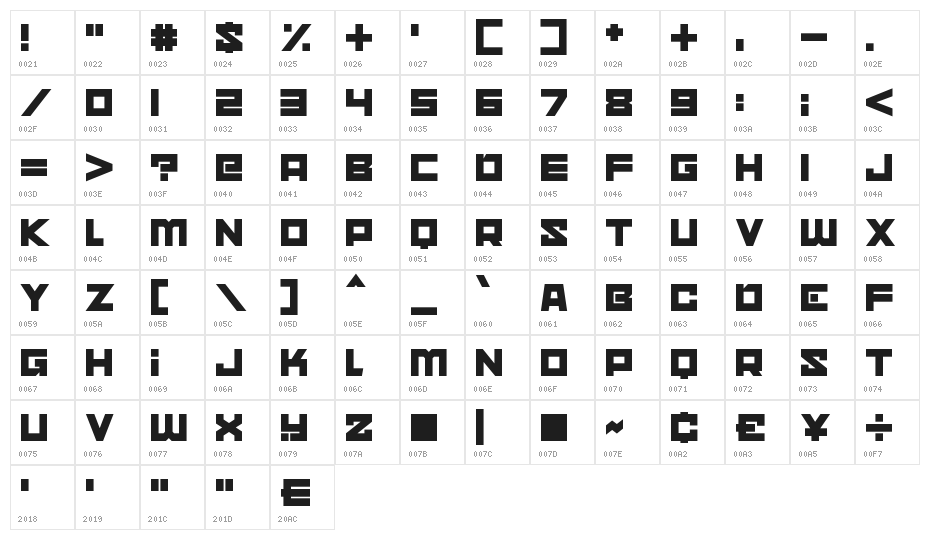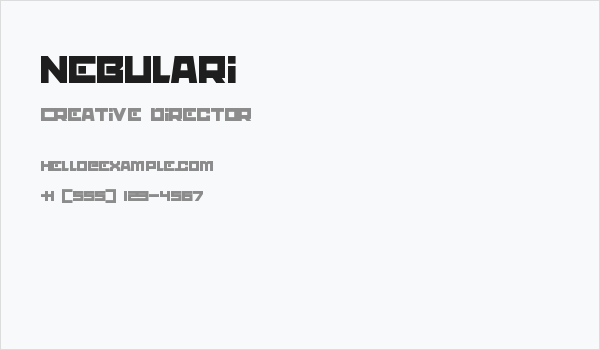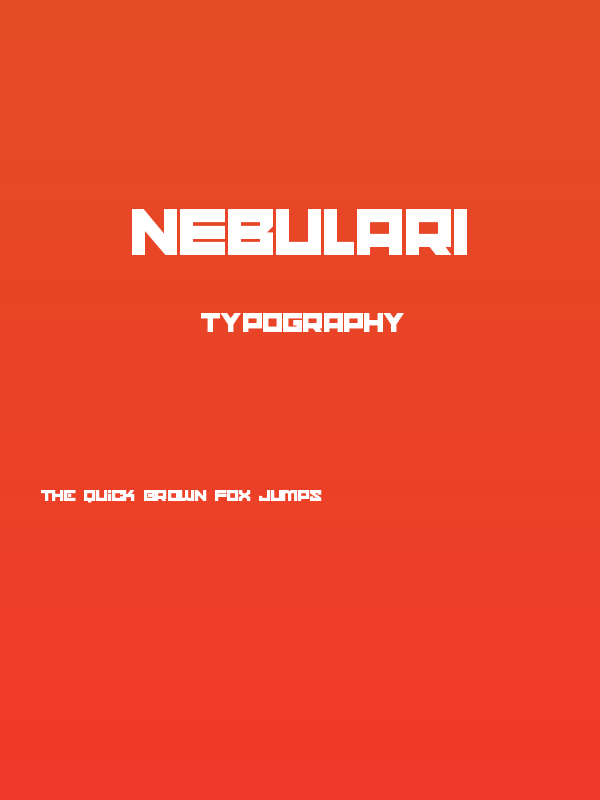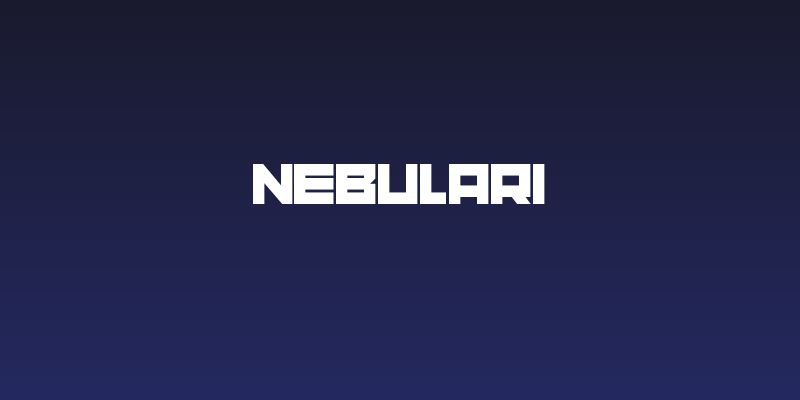
nebulari Font
Darrell Flood
| Vorgeschlagene Projekte | Ideal for tech-related branding, video game titles, sci-fi movie posters, and digital interfaces. |